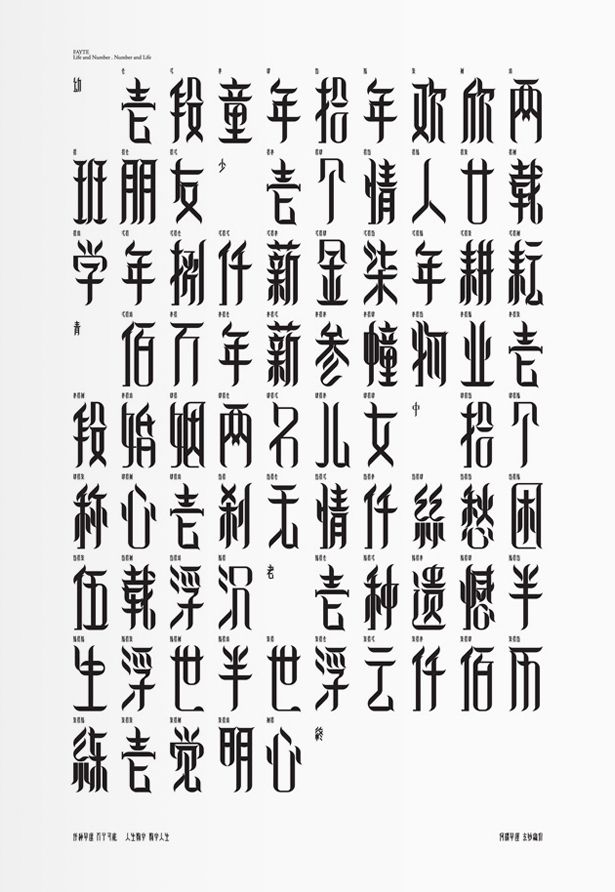
1. Чтобы уточнить, это не были «контурные шрифты», используемые сегодня, созданные с использованием кривых Безье. Это были скелетные шрифты, состоящие из серии прямолинейных отрезков.
Гоань Гу и Джон Д. Хобби. «Использование METAFONT для создания китайских иероглифов». Компьютерная обработка китайского и восточных языков 1 (июль 1983 г.): 4–23.
Хидеюки Хаяси, Шейла Дункан и Сусумо Куно. «Графический ввод/вывод нестандартных символов».